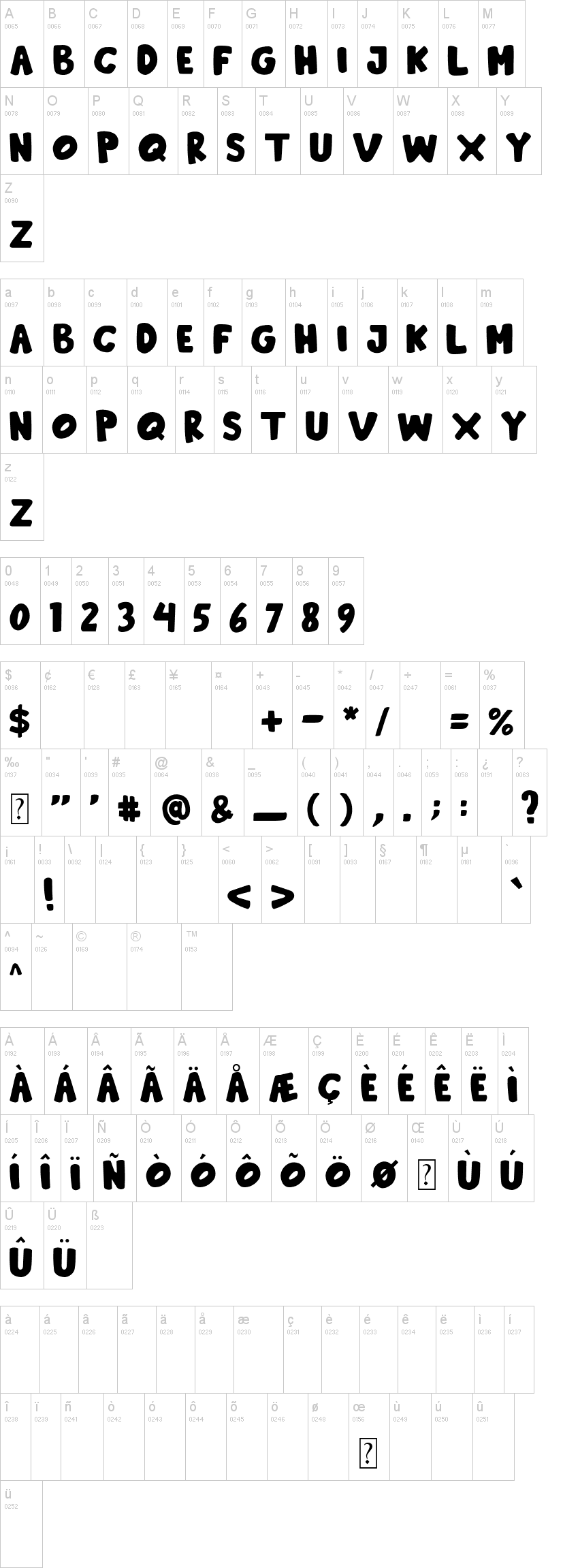
Beachday
Beachday 是一种手写字体,其风格轻松且自然,时尚而随意。它适用于多种场合,比如海滩派对、户外活动、旅游海报等。Beachday 字体具有明亮的外观和良好的可读性,字母形状独特,带有一些手绘的感觉,非常适合在设计中使用。该字体适用于多种语言,可用于印刷和数字设计。如果您正在寻找一种能够为您的设计增添轻松时尚感的字体,那么 Beachday 可能是不错的选择。
Beachday是一款非常不错的手写艺术字体,具有很好的视觉感,适合于文化类的宣传设计、商业类品牌的广告和产品包装设计以及个性化文字排版等较多场景。